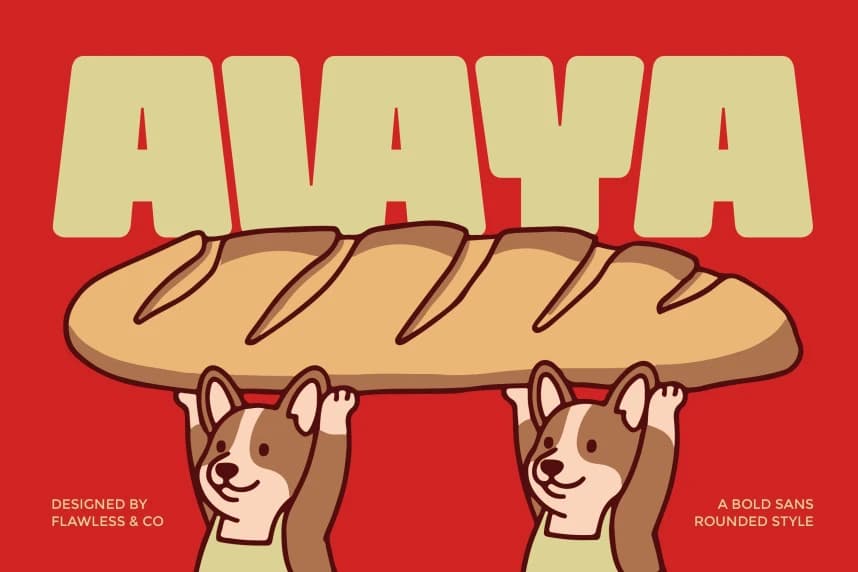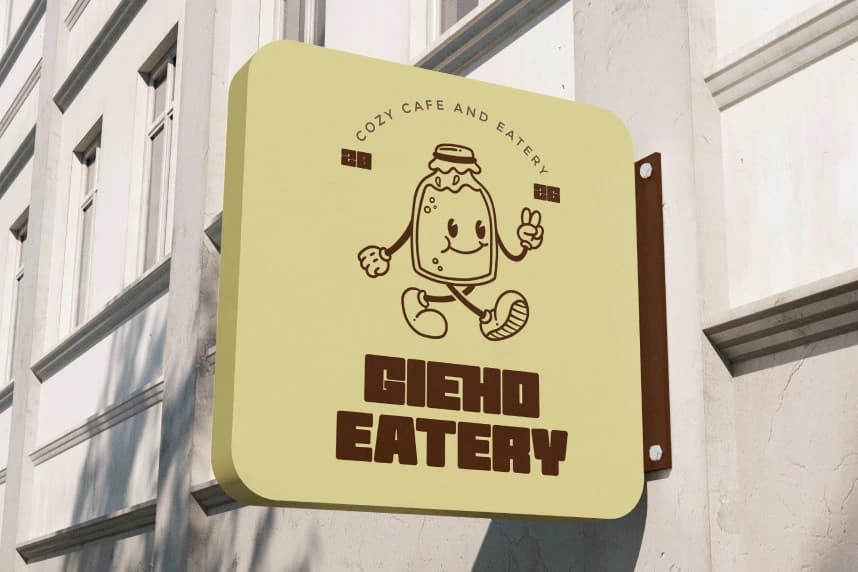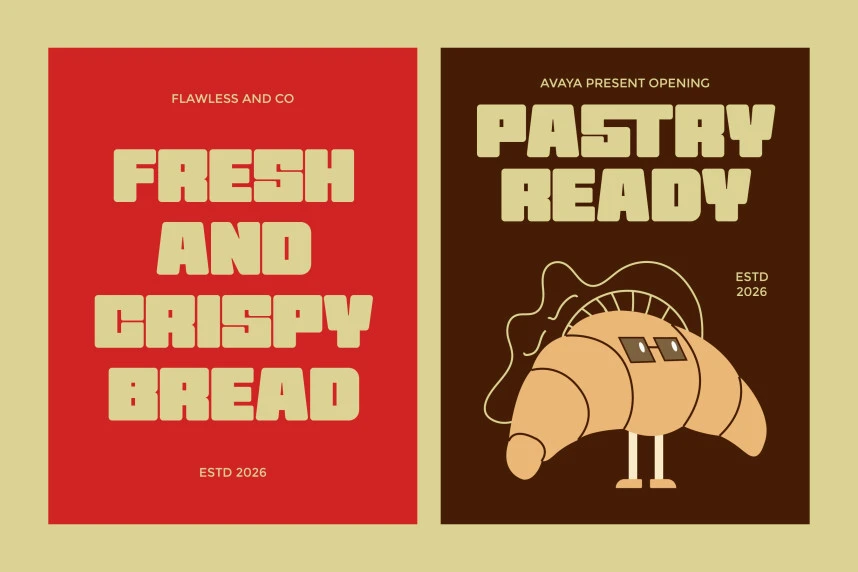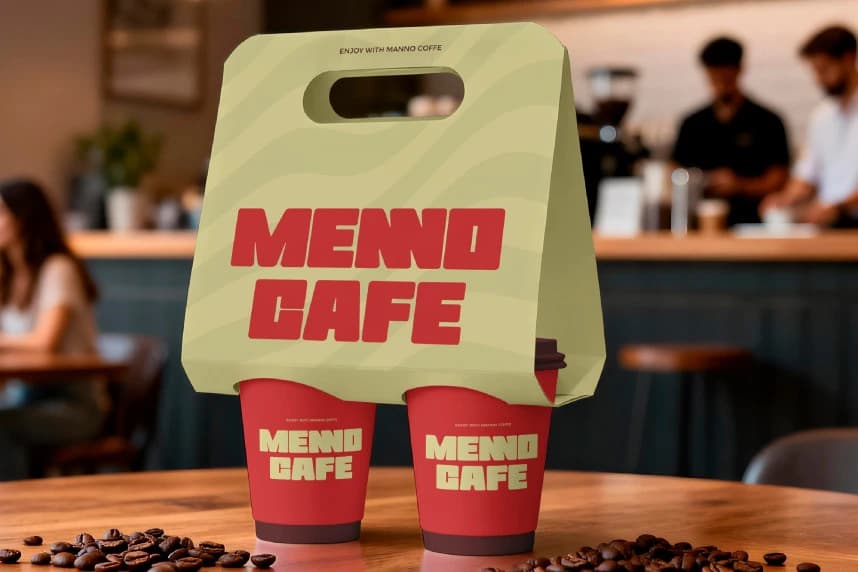
Avaya Font
Avaya Font, güç ile yumuşaklığı modern, kalın ve yuvarlak hatlı bir gösteri sansı yazı tipiyle mükemmel bir denge kuran bir yazı tipidir. Sağlam yapısı ve kavisli kenarları sert hissettirmeden cesur bir etki yaratır ve tipografinize dostça ve ulaşılabilir bir kişilik kazandırır.
Avaya Font, güç ile yumuşaklığı kusursuz bir dengede birleştiren modern, kalın ve yuvarlak hatlara sahip bir gösteri sans tipidir. Sağlam yapısı ve eğri kenarları sert hissetmeden belirgin bir varlık yaratır; tipografinize dostça ve ulaşılabilir bir kişilik kazandırır.